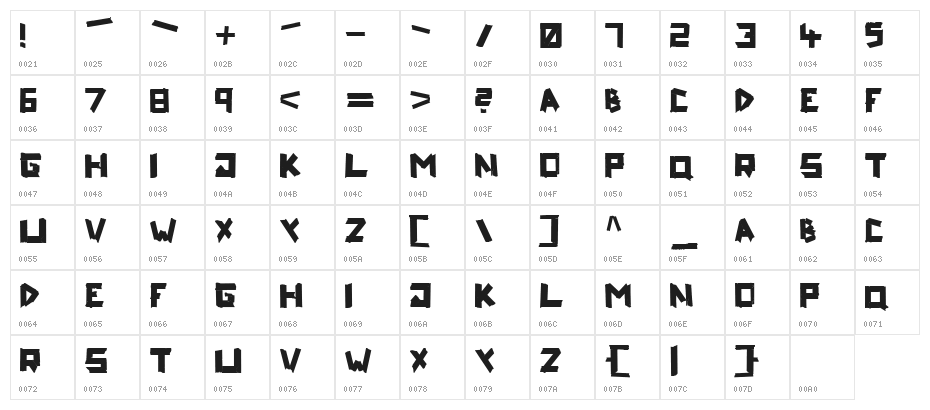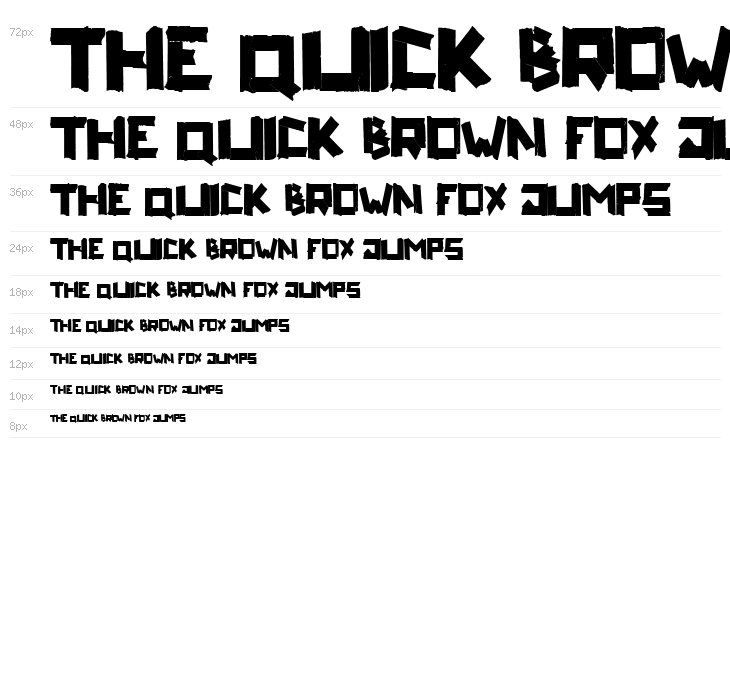
ripTAPE Font
| Stile generale | Urban, Edgy, Modern |
| Progetti proposti | Ideal for street art designs, music album covers, edgy branding, and posters that require a bold statement. |